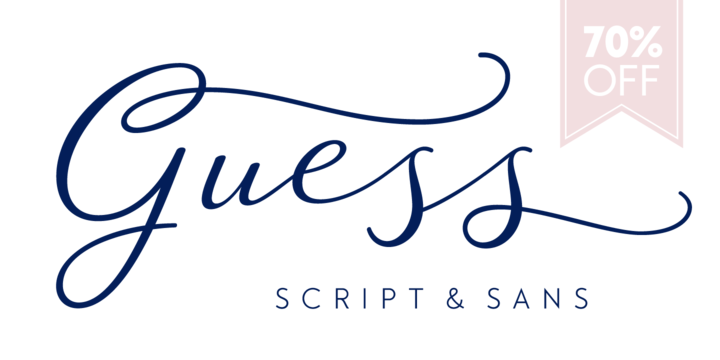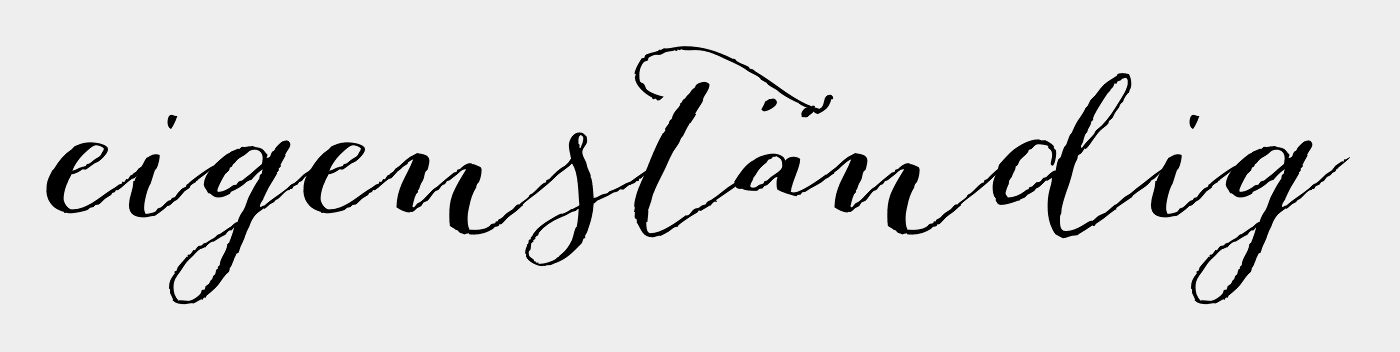
50er Jahre Style, Letterpress Typo - Kennt diese Schrift jemand?
bin neu hier, weil ich vor ein paar Tagen über ein Kärtchen gestolpert bin  mit dieser Schrift drauf und ich für einen Kunstkatalog gern so eine Schrift ins Layout einfließen lassen möchte...
Würd mich freuen wenn mir jemand helfen kann sie zu identifizieren oder eine ähnliche Schrift vorschlagen könnte...!
Das wurde gezeichnet, nicht aus einer Satzschrift gesetzt. Handwerklich eine … hm … sehr eigenständige Arbeit ;-)
Es gibt zur Zeit einige Schriften in diesem Stil neu auf dem Markt – schau Dir doch zum Beispiel mal die Bombshell an.
Wenn Du dann bei MyFonts auf »more Fonts like this« klickst, bekommst Du jede Menge Schriften angezeigt, die auch noch stärker in die von Dir gesuchte Richtung gehen.  :-D
Vielleicht auch die Windsong?
Ihr seid super!!! Dankesehr, ich denk die Bombshell oder die Guess wirds werden....!